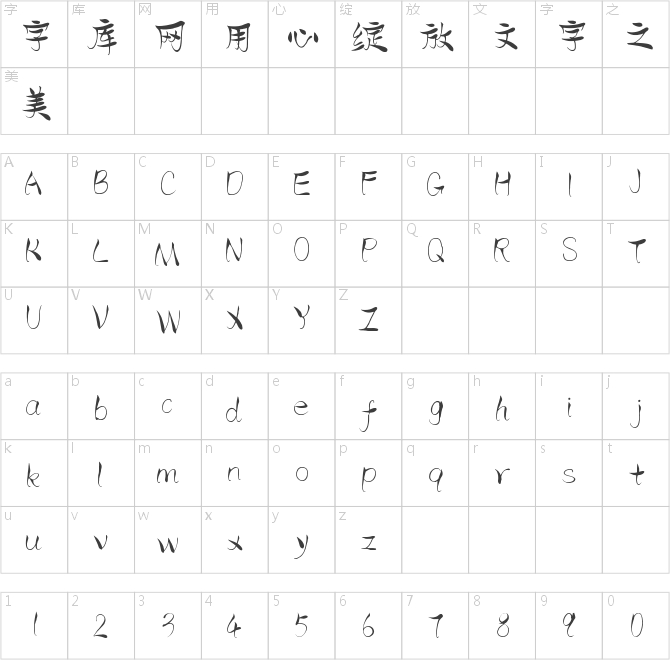
字魂257號(hào)-妙語(yǔ)手書是一款手寫字,字形瘦長(zhǎng),筆畫簡(jiǎn)潔有力,風(fēng)格鮮明,造型巧妙有創(chuàng)新力,有著較好的應(yīng)用空間,適用于品牌廣告和產(chǎn)品包裝設(shè)計(jì),以及社交網(wǎng)絡(luò)的個(gè)性化用字。
字魂257號(hào)-妙語(yǔ)手書字體ZiHun257Hao-MiaoYuShouShu字庫(kù)是一款讓人賞心悅目、百看不厭的中文字體,適合各類廣告和產(chǎn)品包裝設(shè)計(jì)應(yīng)用,字體大小17.6MB,格式為ttf字體,上傳用戶是Elieen,作者/版權(quán)方為字魂